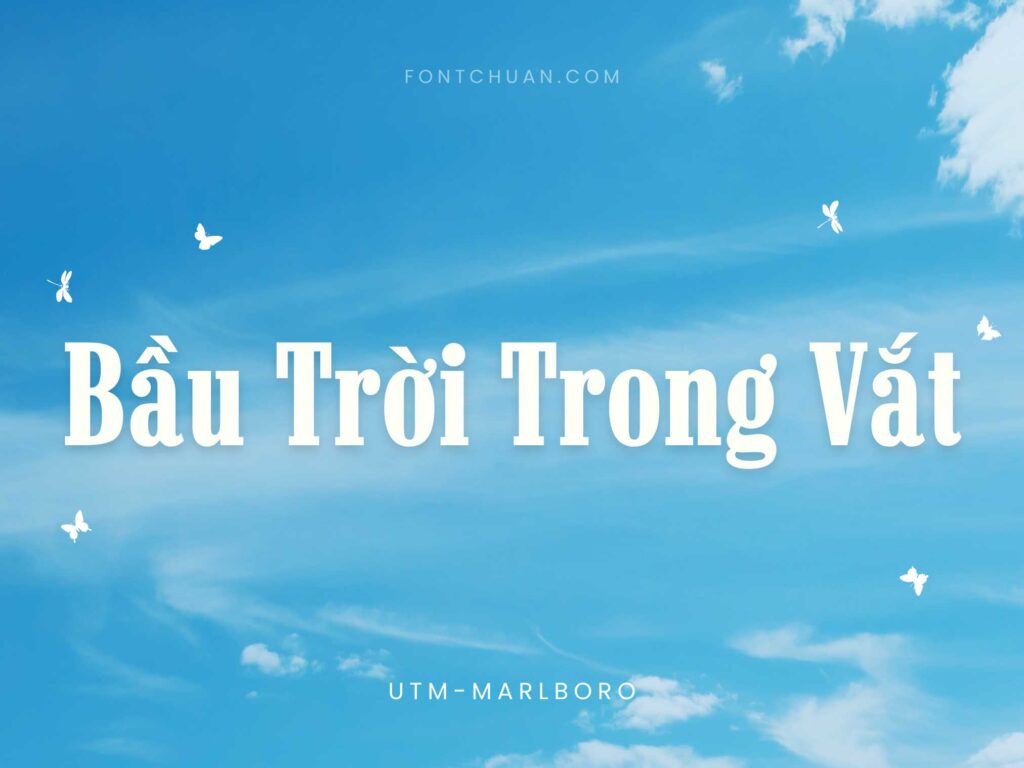
Font UTM Marlboro Việt Hóa
Việt hóa bởi: Thiên Minh
UTM Marlboro là một font chữ mang phong cách cổ điển phương Tây, lấy cảm hứng từ typography đặc trưng của các thương hiệu nổi tiếng. Font này mang đến sự mạnh mẽ, nam tính và đầy cá tính, phù hợp với các thiết kế cần tạo sự ấn tượng và khác biệt. Font đã được Việt hóa bởi Thiên Minh, hỗ trợ đầy đủ tiếng Việt cùng hơn 200 ngôn ngữ khác, giúp mở rộng khả năng sử dụng. Thành viên của Font Chuẩn đã sưu tầm và giới thiệu font này nhằm đáp ứng nhu cầu bạn đọc, cung cấp nguồn tham khảo chất lượng và ứng dụng thực tế vào các dự án thiết kế
Về đặc điểm thiết kế, UTM Marlboro có các nét chữ dày, chắc chắn và đậm chất vintage. Font này phù hợp với nhiều ứng dụng như thiết kế logo, biển hiệu, poster, bao bì sản phẩm và các dự án sáng tạo khác. Các ngành nghề như quảng cáo, ẩm thực, thiệp cưới và công nghệ có thể tận dụng font này để tạo nên sự khác biệt và thu hút trong các ấn phẩm thiết kế